يجب أن تكون على دراية بخط الأرقام بشكل خاص أثناء تصميم الرسوم البيانية أو التقويمات أو التصميمات الأخرى التي تحتوي على رقم.
فقط من خلال خط الرقم الصحيح يمكنك إضفاء لمسة احترافية وفنية على تصميمك أو موقعك على الويب. لحسن الحظ ، هناك العديد من خطوط الأرقام ، وقد يكون من الصعب اختيار الخط المناسب.
1. Dione Room Numbers يعرض عائلة الخطوط
عرض أرقام غرف Dione هو خط Serif غير أبجدي. يركز فقط على الرموز العددية والعملات.
تلهم لوحات أرقام غرف الفندق المطلية الخط. نفس الشيء واضح للعيان من مظهره! إذا كنت تبحث عن خط عرض ، ففكر في عرض أرقام Dione Room.
2. Dropgray
إذا كنت تريد لمسة من الأناقة في تصميمك ، فيجب أن ينتهي بحثك بـ Dropgray. يدعم هذا الخط ما يلي:
- أعداد
- حرف او رمز
- الأحرف الكبيرة و الأحرف الصغيرة
Sarid Ezra هو مبتكر Dropgray ، وهو مثالي لأي تصميم راقي. بالإضافة إلى ذلك ، يدعم الخط ميزة متعددة اللغات وهي ميزة إضافية.
استخدم Dropgray إذا كنت ترغب في إضافة لمسة السبعينيات في تصميمك
3. Okami
Okami هو خط فرشاة مثالي لتصميم عصري وأنيق. إن USP of Okami هو أنه يعطي مظهرًا للخط المرسوم يدويًا بلمسة من الحافة الخشنة.
يمكنك استخدام Okami إذا كنت بحاجة إلى تدوين:
- أعداد
- الأحرف الكبيرة
- رسائل متعددة اللغات
- علامات ترقيم
يدعم الخط العديد من الأنماط البديلة لمعظم الحروف.
4. إزميل
درو ميلتون هو مصمم الخط الإزميل. مرة أخرى ، إنه خط غير أبجدي يمكنك استخدامه في شاشات النوافذ والملصقات.
الخط متوفر بثلاثة أنماط مختلفة. نوصي بهذا الخط إذا كنت تريد استخدام رموز الأرقام الصلبة فقط في تصميمك.
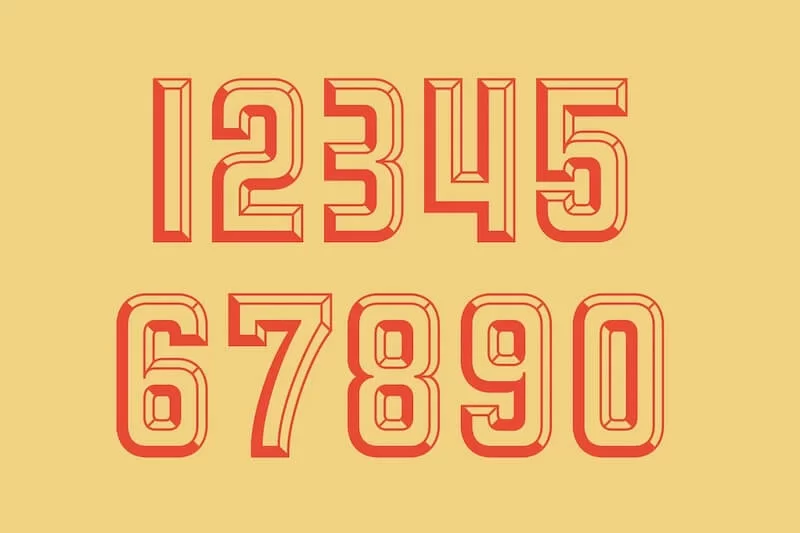
5. المراوغة
Quirk هو اسم خط غير تقليدي. المنحنيات في الأرقام هي التي تجعل هذا الخط فريدًا.
يمكنك استخدام خط Quirk من أجل:
- أعداد
- الشخصيات الخاصة
- جميع الأحرف الاستهلالية والأحرف الصغيرة أحرف بديلة
المجموعة البديلة للخط سهلة الاستخدام لصياغة تصميمات فريدة.
6. الحبيبات الغربية
ينتمي Western Grit إلى عائلة Serif ، وهو يعطي نظرة حزينة على الأرقام. إنه خط مرسوم يدويًا يعطي إحساسًا بالأسلوب القديم.
سيبدو Western Grit جيدًا على اللافتات والملصقات التي تحتاج إلى مظهر عتيق. بالإضافة إلى الأرقام والرموز ، يمكنك أيضًا استخدامها لكتابة الأحرف الأساسية وعلامات الترقيم.
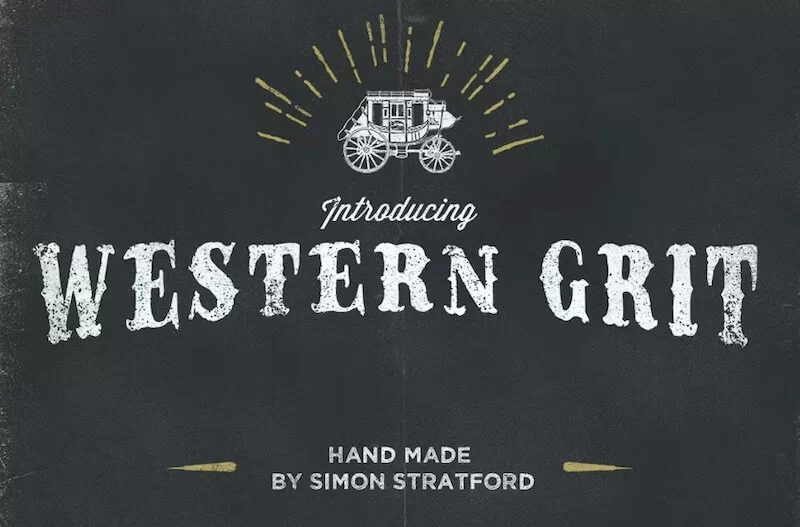
7. جيسيتو
Gessetto هو الخط المثالي للمشاريع الصديقة للأطفال. يأتي من عائلة خطوط الطباشير ، يكمن USP لـ Gessetto في التباين الذي يحمله في كل من الملمس والأسلوب.
8. أرقام كليمنت
هذا الخط مستوحى من 1838 Type Specimen Book ، الذي أصدره المصمم Fonderie Clement.
تعطي الدوامة الحلزونية للأرقام جوهرًا لخط أرقام كليمنت.
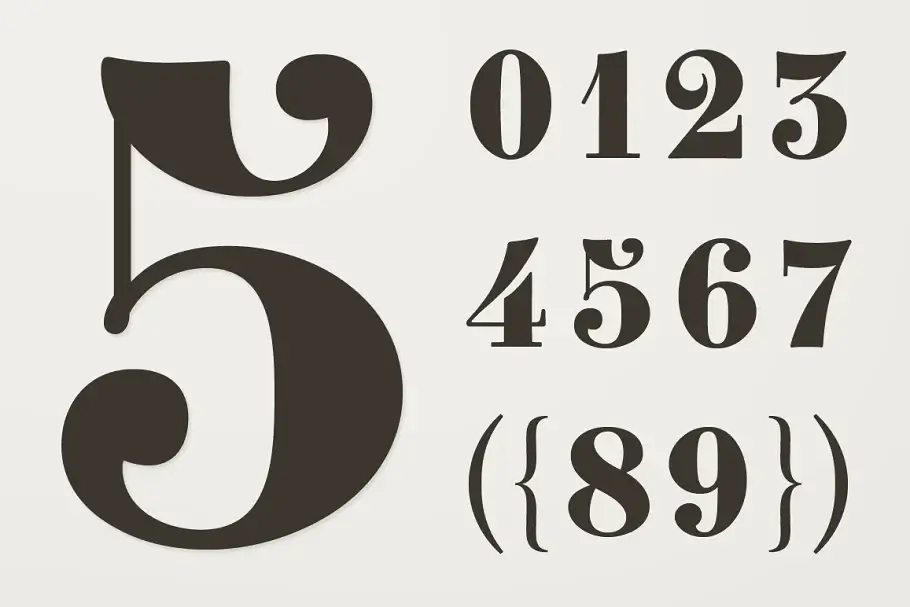
9. رتابة
سيذكر النمط المرئي لـ Monoton القراء بخطوط الضغط المعدنية في الثلاثينيات. على الرغم من أن Monoton مصمم لمتصفحات الويب ، إلا أنه يناسب النشرات الإعلانية بشكل أفضل.
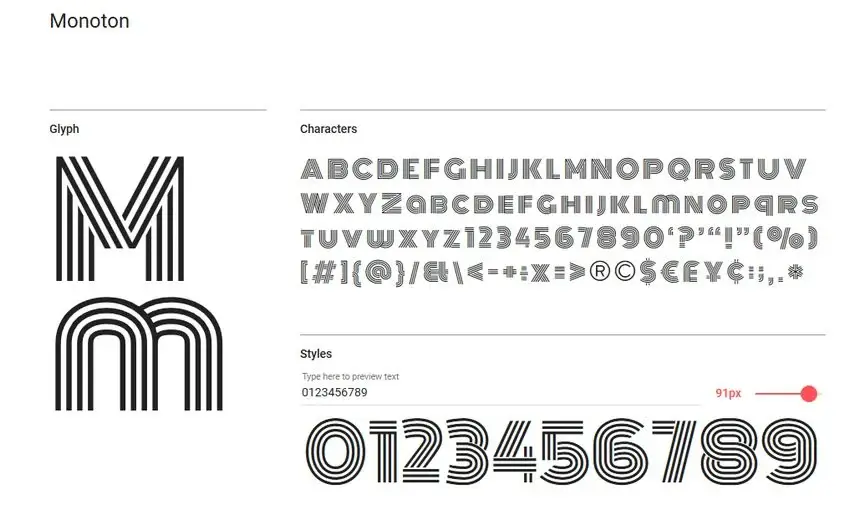
10. جاك فرانسوا شادو
استلهم Cyreal ، مصمم Jacques Francois Shadow ، الخط من Jacques Francois Rosart. إن تأثير الظل للنص يجعله بارزًا في جميع الوسائط تقريبًا.
جاك فرانسوا شادو هو الأنسب للتصاميم ذات أحجام الطباعة الكبيرة
11. خط CombiNumerals
خط CombiNumerals هو خط كتلة للأرقام. يمكنك استخدام هذا الخط لإنشاء رقم دائرة.
من الأفضل تصميم رسومات الويب والكتيبات الإرشادية.
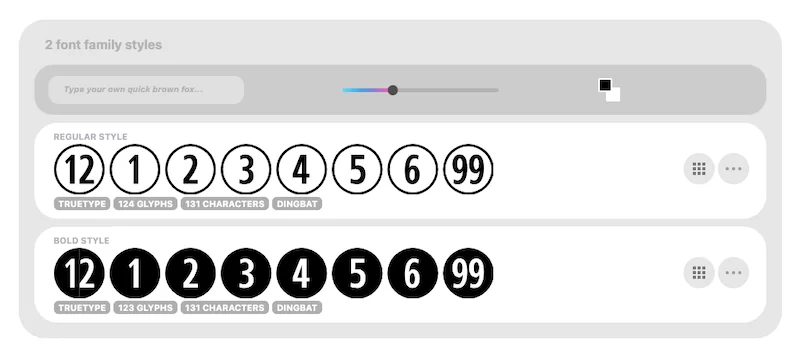
12. بورمون
Beurmon هو خط ذو حافة مستديرة بلمسة هندسية. يمكنك استخدام هذا الخط للأرقام والرموز. ومع ذلك ، على الرغم من أنه يدعم لغات متعددة ، إلا أنه لا يمكن استخدامه إلا للأحرف الكبيرة.
يمكنك استخدام Beurmon في الكتابات التي تتطلب نصًا كبيرًا ، مثل العناوين والنصوص المستخدمة على أغلفة المجلات.
13. إمبر
نمط الخط هذا للأرقام متاح بنمطين مختلفين. إنه خط استنسل كبير يساعد في إنشاء عناوين مؤثرة.
بالنظر إلى أنه نص كبير الحجم ، يمكنك استخدام Ember لتصميم الملصقات والنشرات الإعلانية.
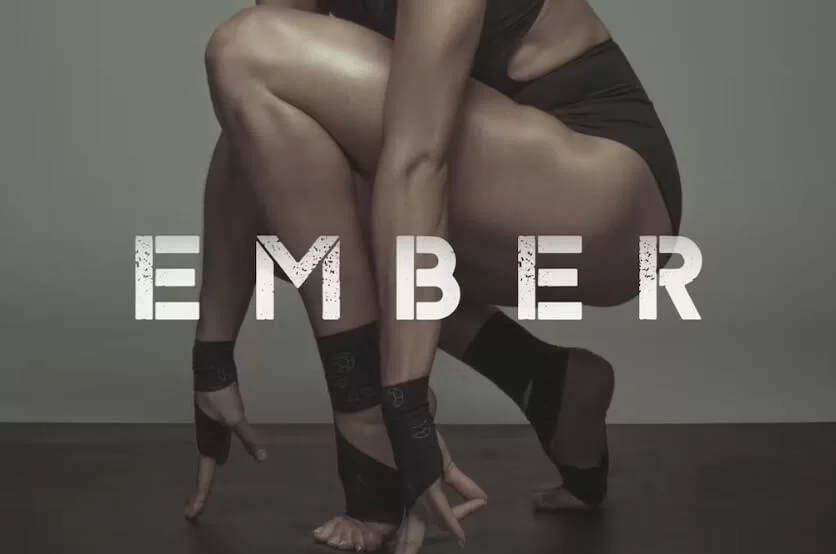
14. هيكو إنلاين
Hikou Inline هو خط عتيق جميل يعمل بشكل رائع مع العناوين. بالإضافة إلى كتابة الأرقام ، يمكنك أيضًا استخدامه للأحرف الكبيرة متعددة اللغات.
يمكنك استخدام التصميم الفريد لـ Hikou Inline لصياغة منشورات وسائل التواصل الاجتماعي بمظهر جمالي.
15. كومار واحد
يتميز Kumar One بضربات رأسية عريضة بخطوط أفقية أرق. بالإضافة إلى ذلك ، فإن الزاوية 45 درجة عند زوايا رقم Kumar One تجعلها تبدو أفضل.
يبدو نظيفًا وزخرفيًا في نفس الوقت ، مما يؤدي في النهاية إلى مظهر احترافي.
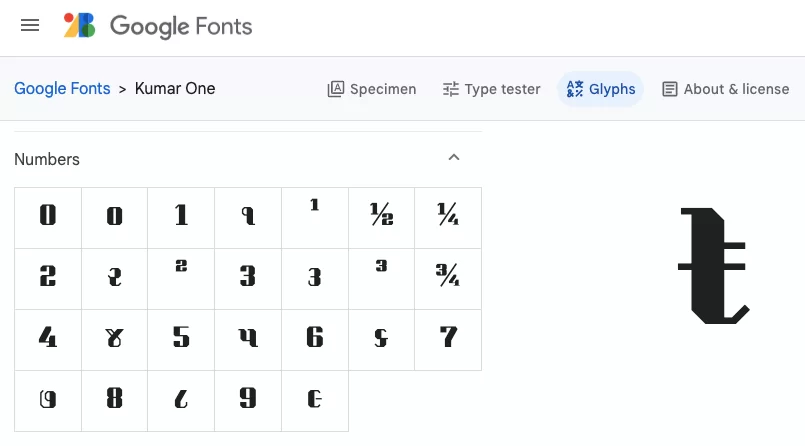
16. المعيار القديم TT
ماذا تتوقع من المعيار القديم TT؟ حسنًا ، بالنسبة للكثيرين ، فإنه يثير شعورًا بالحنين إلى الماضي من خلال إعادتهم إلى القرن العشرين.
إنه مزيج من أساليب serif وأساليب sans-serif الحديثة. يبدو الخط نظيفًا ، ويمكنك استخدامه على موقع ويب يريد خطًا بسيط المظهر.
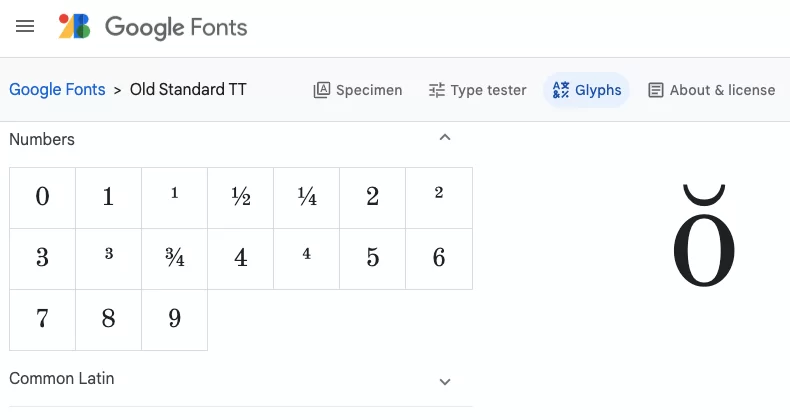
17. اضغط على ابدأ 2P
اضغط على Start 2P هو خط رائع سيحبه اللاعبون بالتأكيد. نمط البكسل للخط يجعله مناسبًا لتصميم أي شيء متعلق باللعبة.
تصميم Copse المتباين يجعلها مناسبة لكتابة المدونات
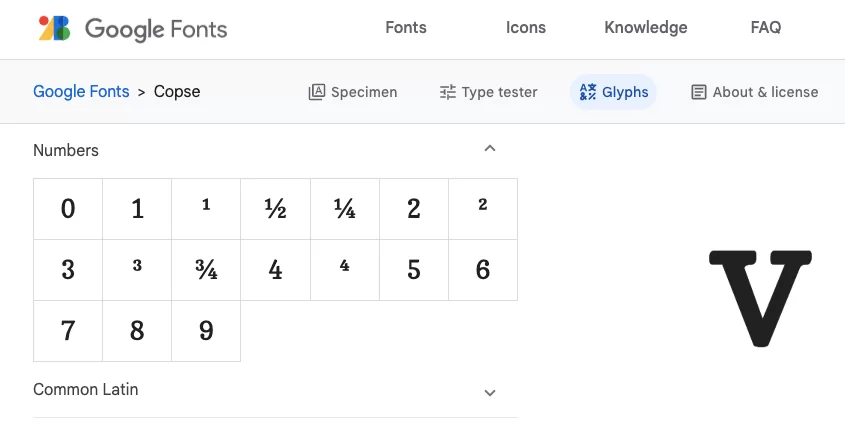
29. خريج
نوصيك باستخدام برنامج Graduate في أي شيء متعلق بالتعليم. تصميم نمط الكتلة للخريجين يجعلها مناسبة لأي عمل جامعي.
30. بوبينز
تنتمي Poppins إلى عائلة sans-serif. إنه مناسب لتصميم كل شيء تقريبًا بسبب تصميم الشكل الممتاز.
يدعم الخط العديد من اختلافات الوزن. يمكنك تجربة الاختلافات والاستقرار على الشكل الذي يناسب التصميم.